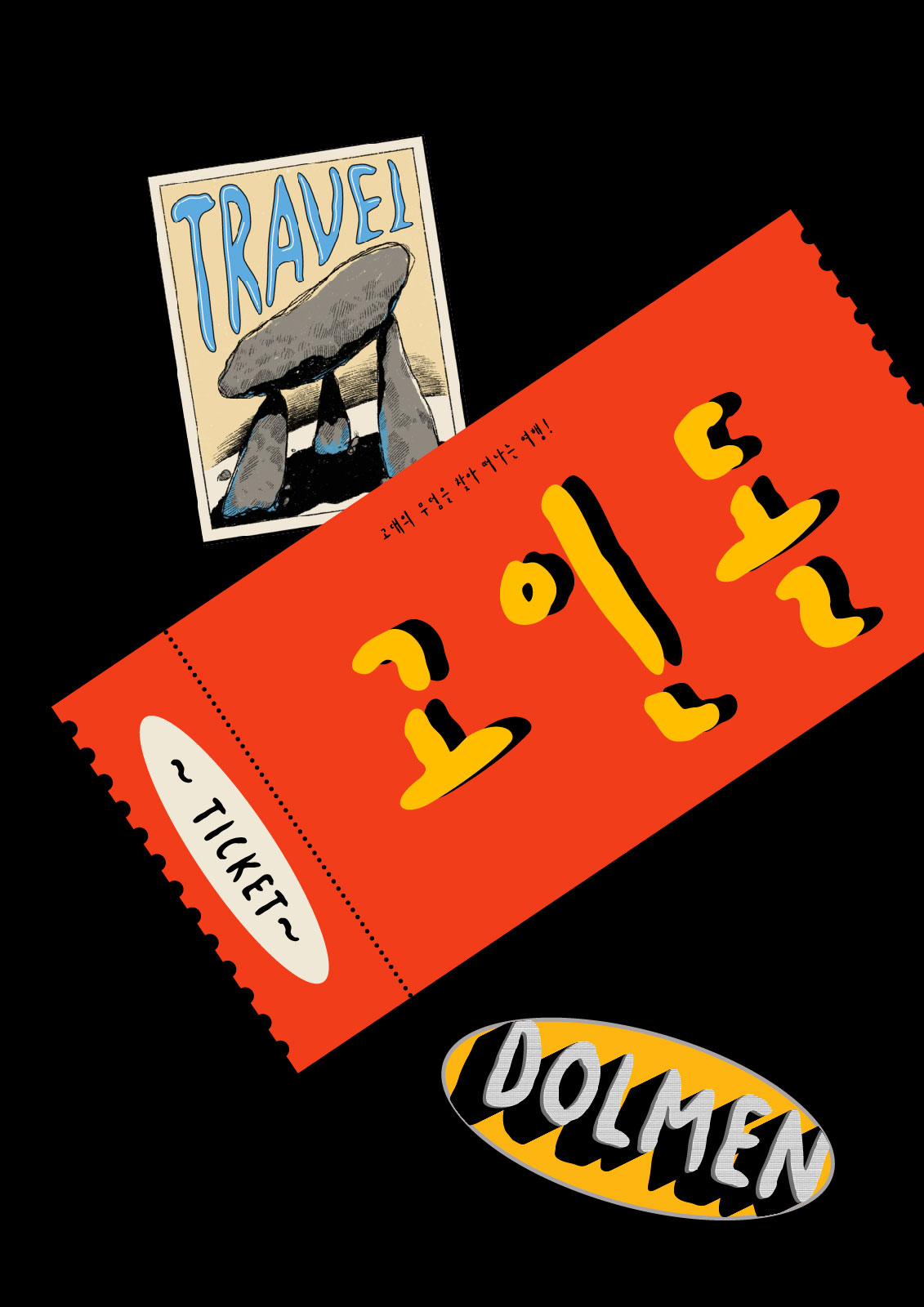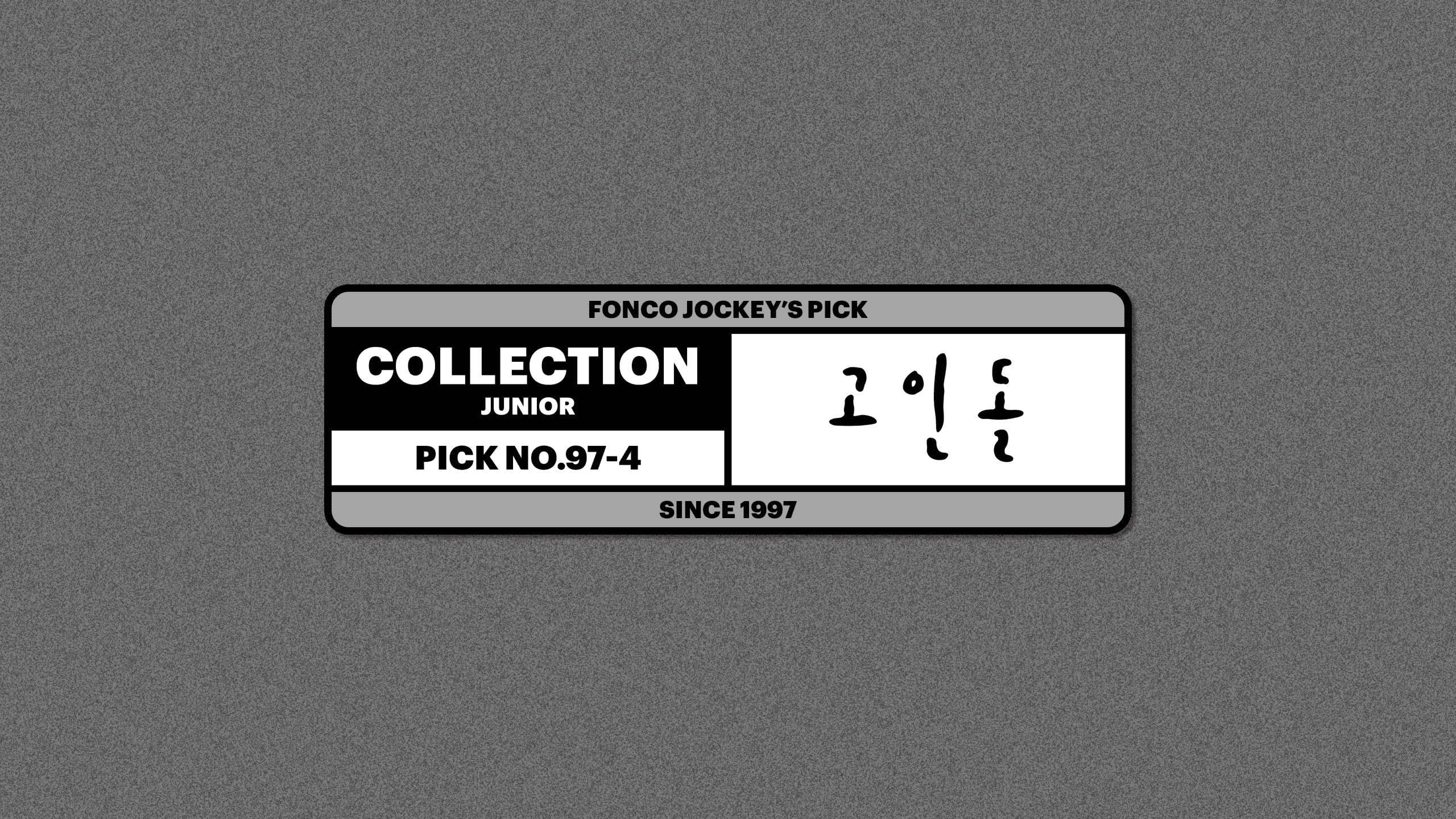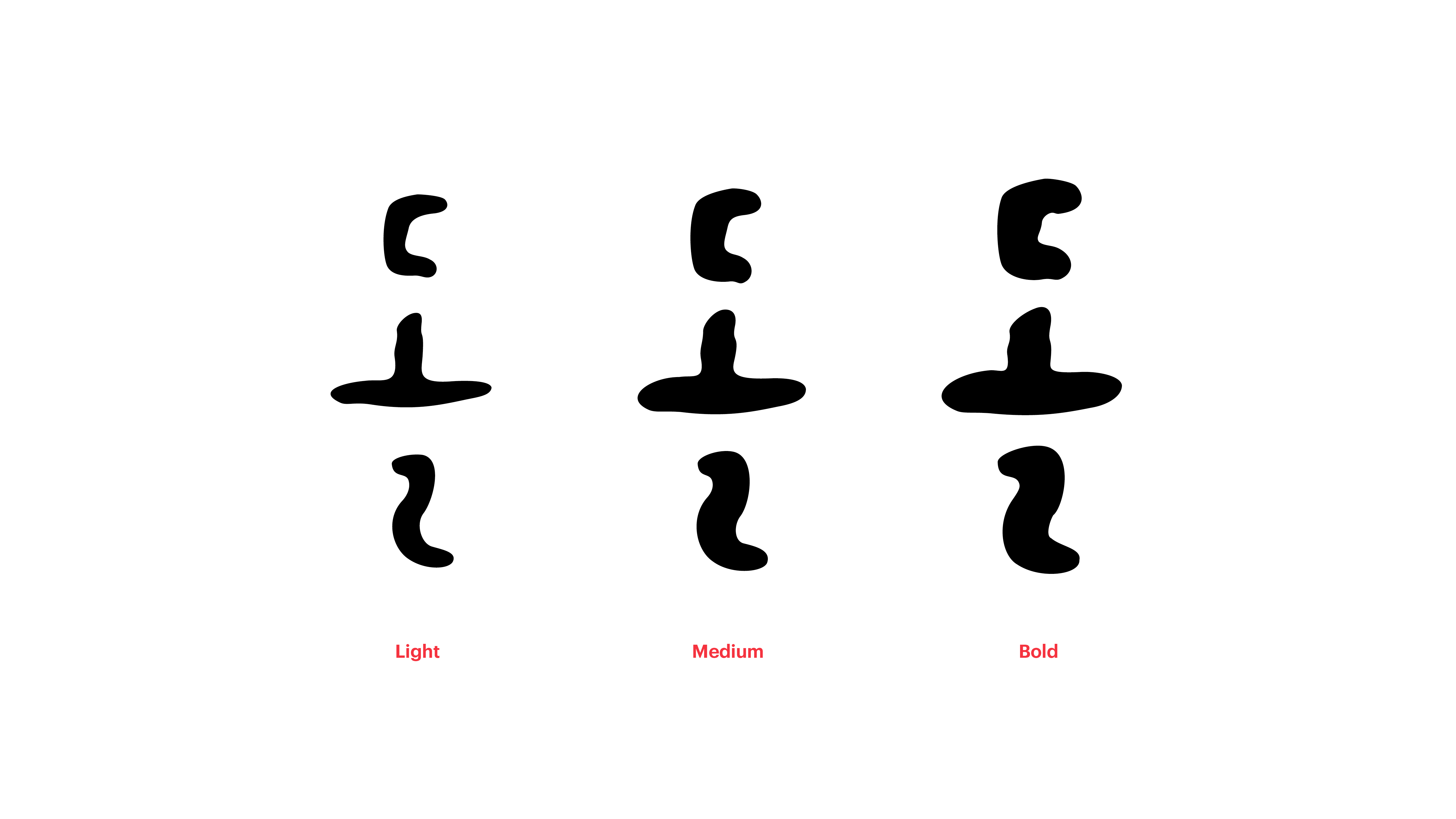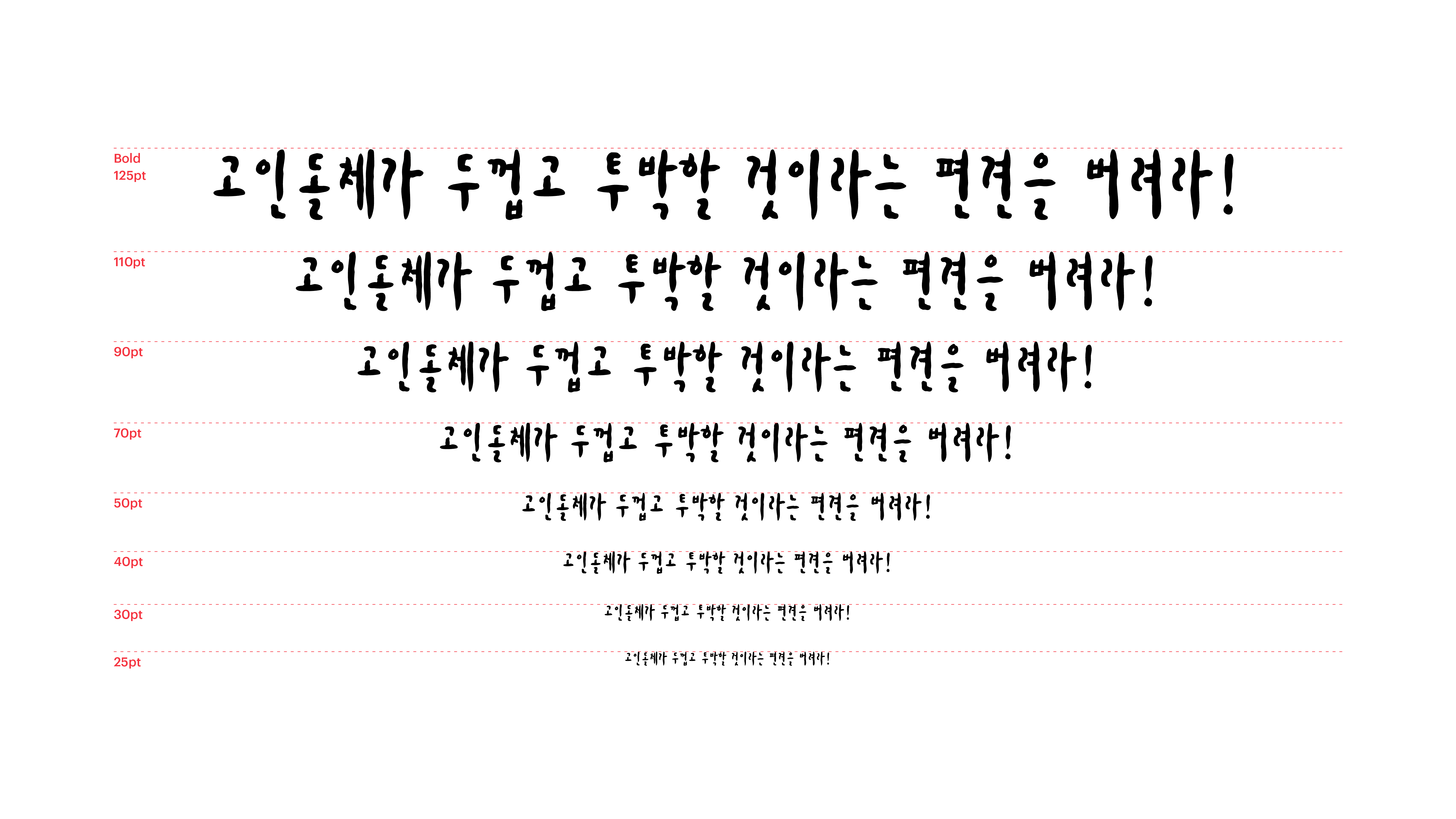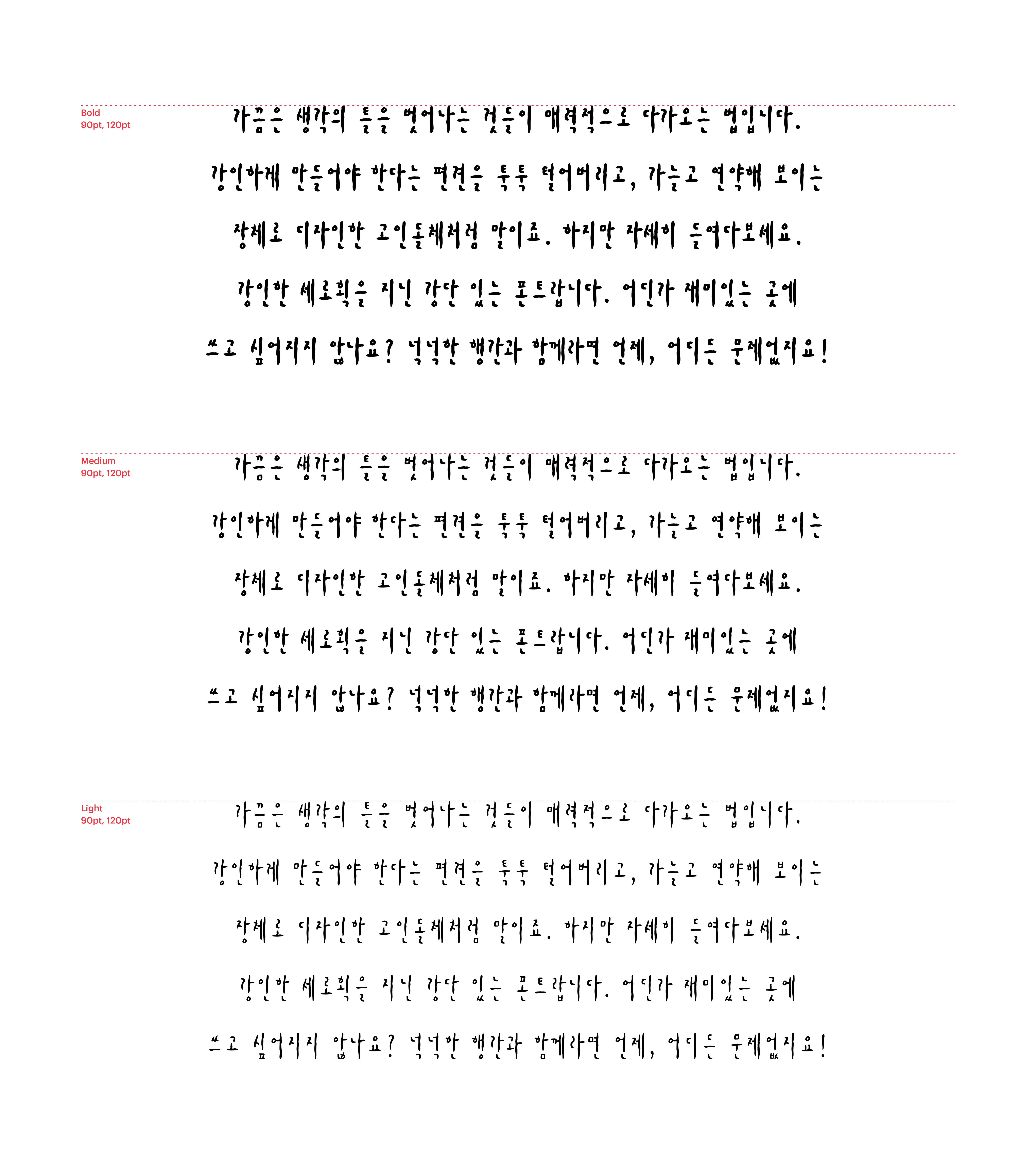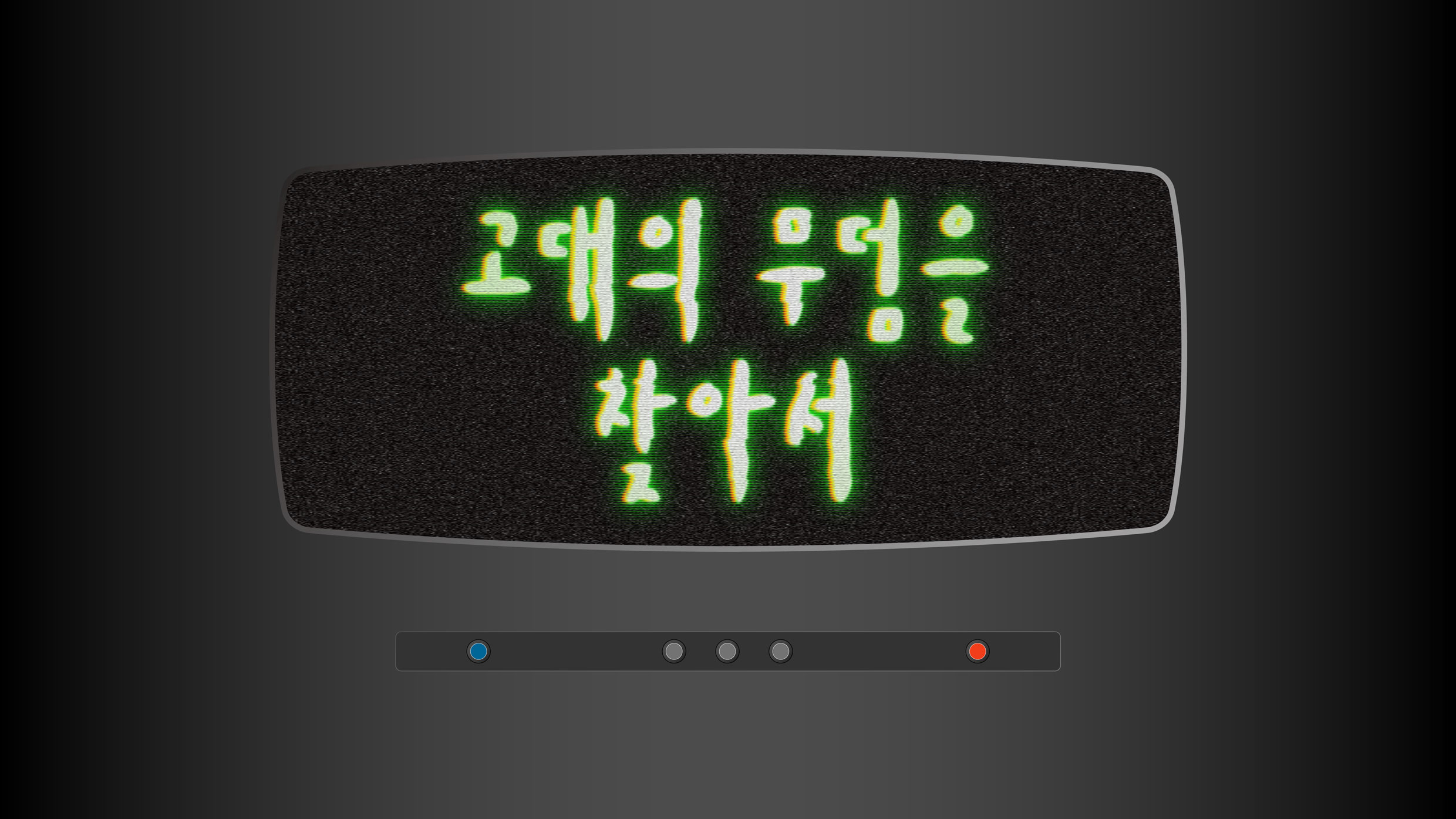
가끔은 생각의 틀을 벗어나는 것들이 매력적으로 다가오는 법입니다. 강인하게 만들어야 한다는 편견을 툭툭 털어버리고, 가늘고 연약해 보이는 장체로 디자인한 고인돌체처럼 말이죠. 하지만 자세히 들여다보세요. 강인한 세로획을 지니고 있는 강단 있는 폰트랍니다. 어딘가 재미있는 곳에 쓰고 싶어지지 않나요? 넉넉한 행간과 함께라면 언제, 어디든 문제없답니다.
Yoon 고인돌